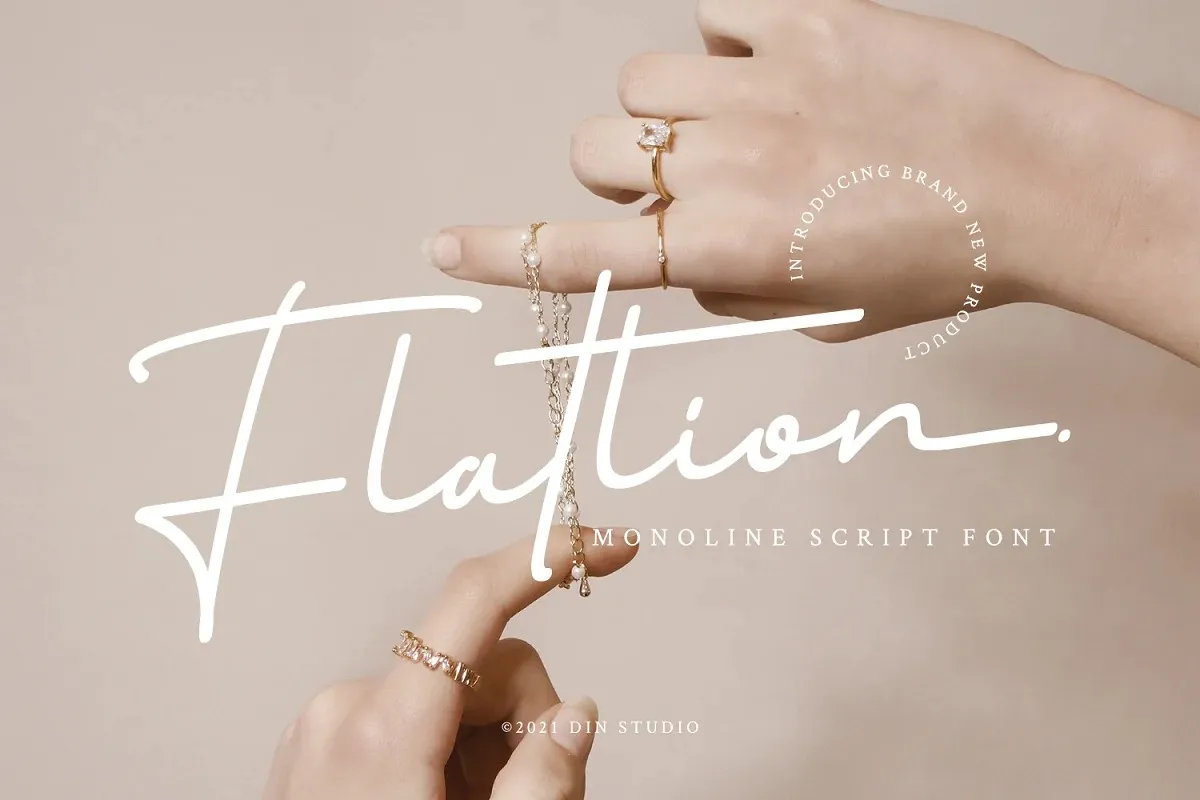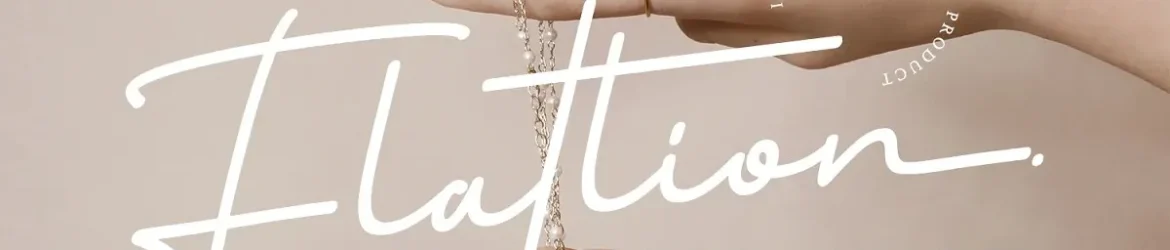
A Flatlion Font é uma elegante mistura de script e mão escrita criada pelo Din Studio para designers que buscam um estilo moderno, refinado e angelical. Este tipo mistura linhas cuidadosamente elaboradas com curvas perfeitamente moldadas, resultando em uma fonte pronta para qualquer projeto que exija elegância e sofisticação. A Flatlion é ideal para banners nas mídias sociais ou postagens, design de anúncios impressos, citações imprimidas, convites, criação de desenhos de camisetas com estilo moderno, embalagens personalizadas e qualquer texto overlay que você desejar adicionar à uma imagem de fundo. A Flatlion é o tipo perfeito para quem quer criar um design que destaca a sua propriedade enquanto mantém uma aparência elegante e sofisticada em todas as mídias digitais.